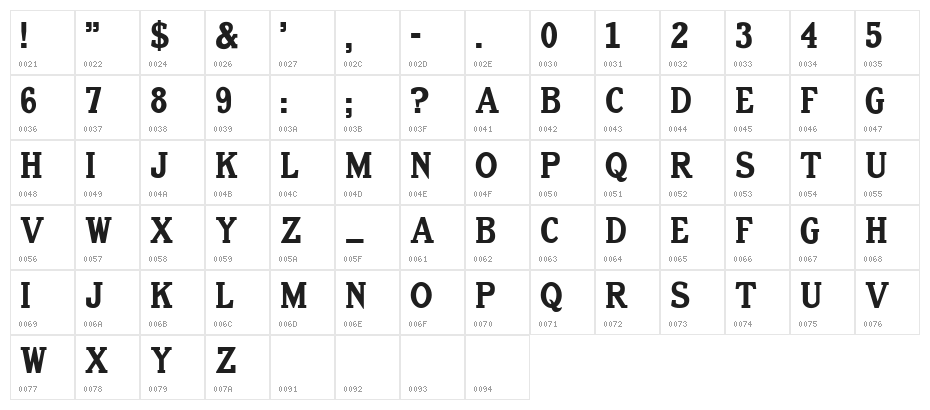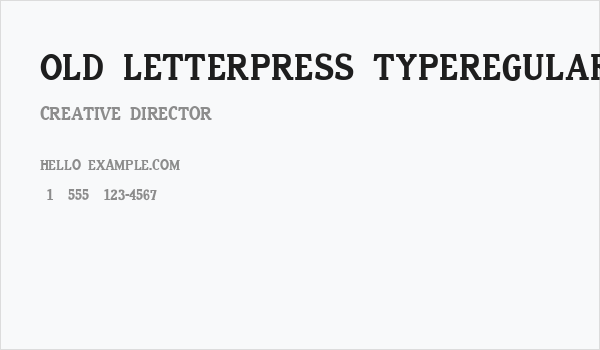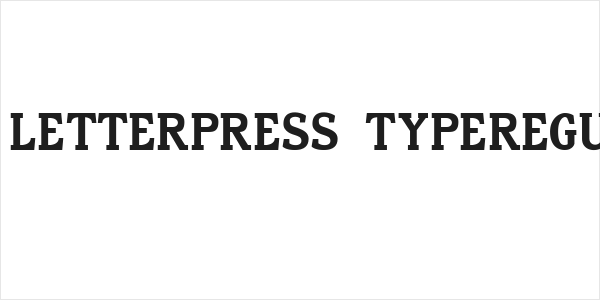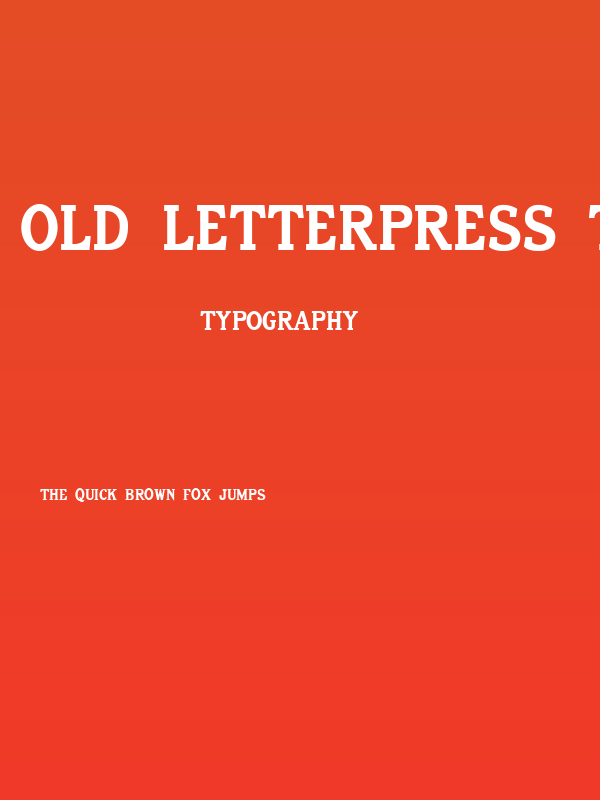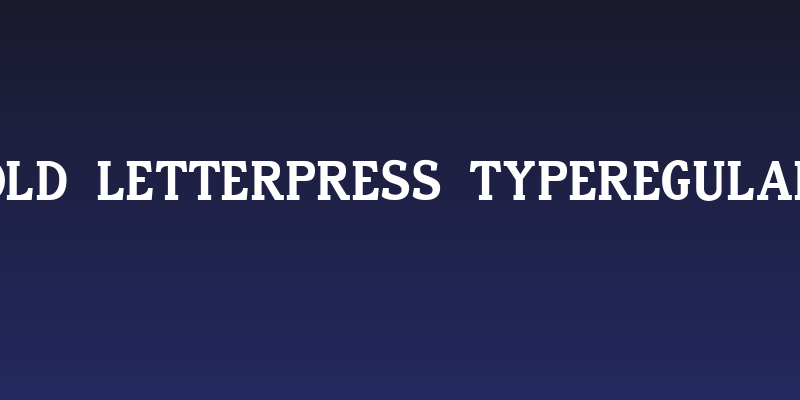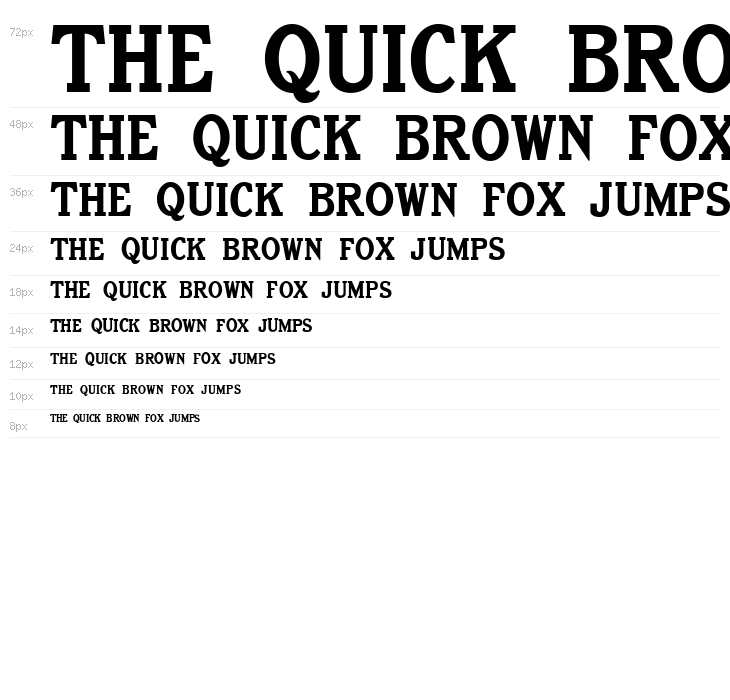
Old Letterpress TypeRegular Font
| おすすめプロジェクト | Ideal for vintage-themed designs, posters, book covers, and branding materials that require a strong, authoritative presence. |